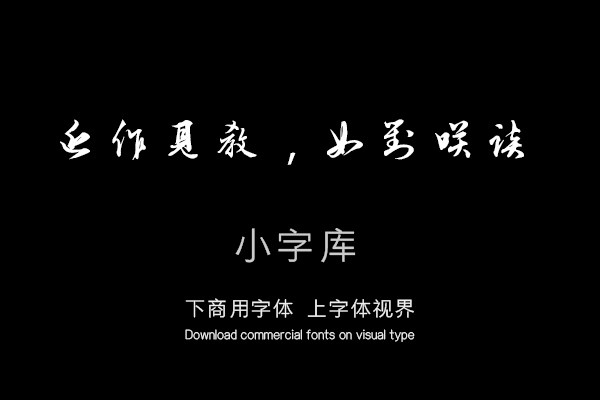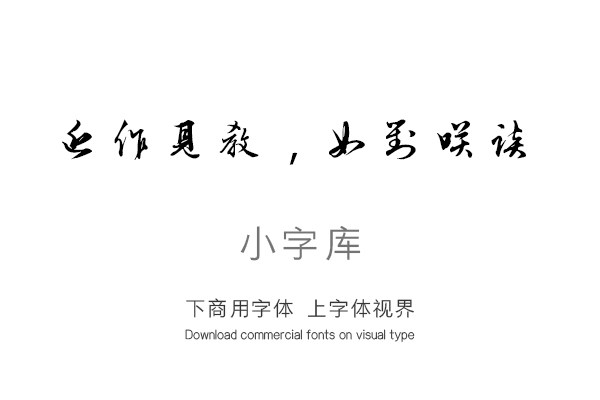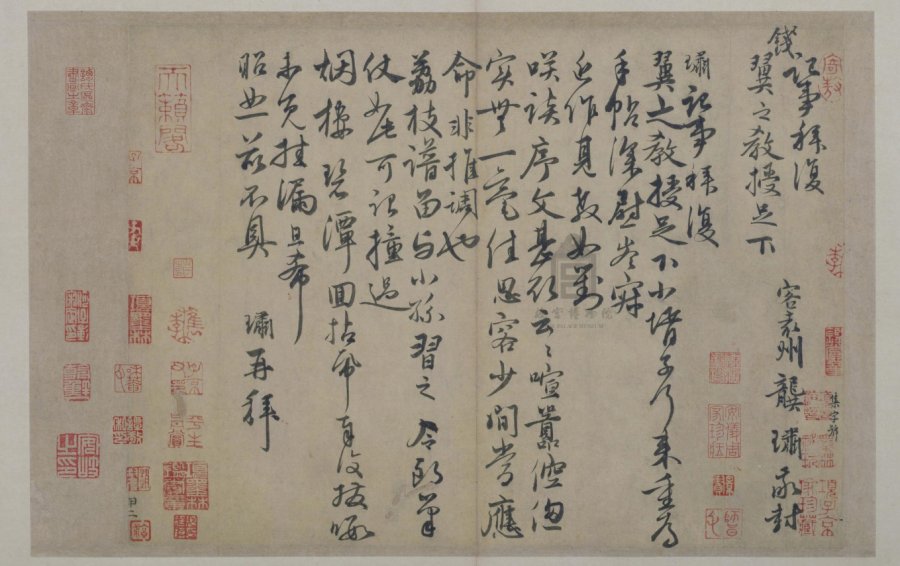
《汉标龚璛行书教授帖》是一款根据元代书法家龚璛经典行书作品《教授帖》,经过再次调整制作的小字库,该小字库共收录了该真迹作品中约144个字体。单字授权
记事拜复钱翼之教授足下,客袁州龚璛敬封。璛记事拜复翼之教授足下。小婿子行来,重为手帖,深慰岑寂。近作见教,如对笑谈。序文甚欲云云,喧嚣倥偬,实无一毫佳思,容少间尝应命,非推调也。《荔枝谱》留与小孙习之。令郎笔仗如此,可谓撞过烟楼。碧潭回,拈纸奉复。拔暇未觅挂漏,且希昭恕,兹不具。璛再拜。